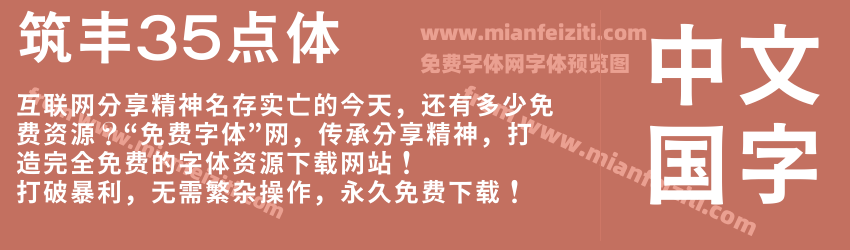
筑丰35点体
字体名称: 筑丰35点体
Postscript名称: Tsukuhou-35Point-Gothic
丰35点体(築豊35ポイントゴチック)是一款以源石黑体创造设计的日式免费可商用字体,该字体以虚构字体“Tsukiji 35 point Gothic”存在时会发生什么情况为主题。假名结构基于 Minyusha 的 35 点 Mincho(筑地的 36 点系统)。这是一种以前从未见过的旧式哥特式字体,我试图尽可能地保留原版的丰富笔触和风格。西方字符源自排字员中常见的独特平衡(我希望这是有道理的)。总体来说,墨水堆积较轻。
除假名、一些标点符号和字母外,使用的字体来自源石黑体,它是思源黑体的衍生字体。
本款“筑丰35点体”是一款书写很新颖的字体,字体大方,适合各种设计作品使用!欢迎下载!